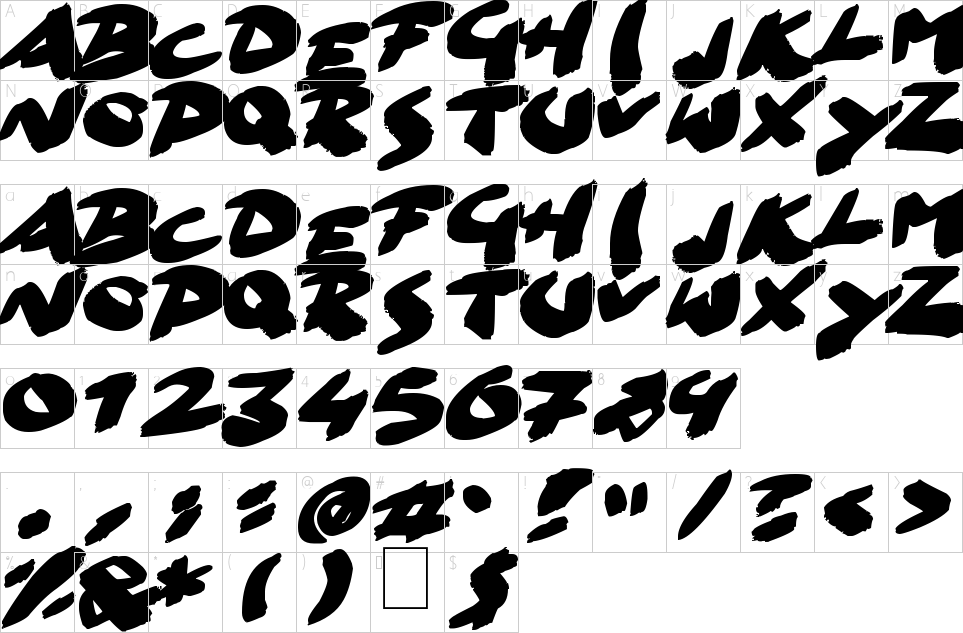
Go Faster Brush Font – Download Grátis
Descubra a velocidade com que pode ser rápido e inovador ao usar a Go Faster Brush Font. Esta elegante fonte é perfeita para quem busca um estilo brusco e dinâmico, combinando facilmente textos e designs gráficos de maneira impressionante. Desenvolvida por Darrell Flood, a Go Faster Brush foi uma escolha inteligente de muitos designers ao procurar uma solução moderna que se destacasse entre as demais. Desde sua disponibilização gratuita para Windows e Mac, a fonte já foi baixada 2074 vezes. Experimente a versatilidade desta ferramenta gráfica sem comprometer o seu orçamento ou tempo. Transforme cada projeto de design em uma obra-prima com a Go Faster Brush Font.